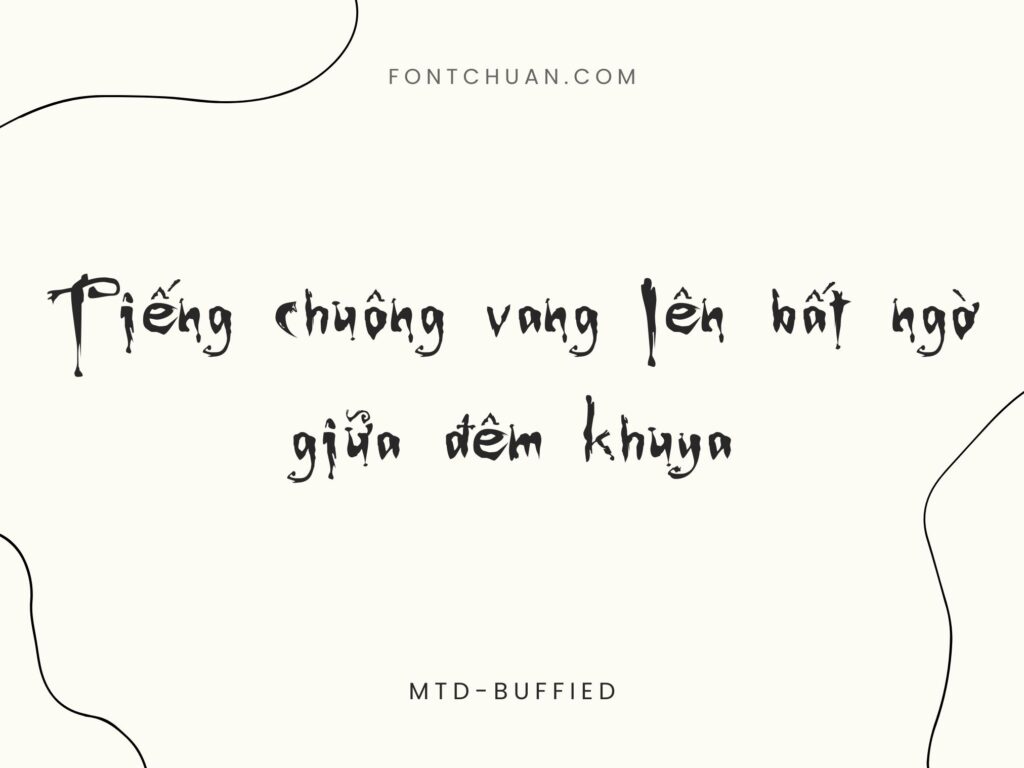
Font MTD Buffied Việt Hóa
Font MTD Buffied là một kiểu chữ trang trí mang phong cách Font Gothic, được thiết kế bởi GemFonts và đã được Việt hóa bởi Mộc Hạ. Font này hỗ trợ đầy đủ tiếng Việt cùng hơn 90 ngôn ngữ khác, mở rộng khả năng ứng dụng trong các thiết kế đa ngôn ngữ. Đây là một trong những phông chữ được cộng đồng thiết kế đánh giá cao và sử dụng trong nhiều dự án sáng tạo, đáp ứng nhu cầu đa dạng của người dùng.
MTD Buffied nổi bật với các đường nét độc đáo và phong cách ma mị, tạo cảm giác huyền bí và ấn tượng. Font rất phù hợp cho các thiết kế liên quan đến chủ đề kinh dị, Halloween, tiêu đề phim, bìa sách, poster và các ấn phẩm đòi hỏi sự khác biệt. Các ngành nghề phù hợp bao gồm quảng cáo, giáo dục, công nghệ và thiệp cưới. Font này cũng lý tưởng cho các sự kiện như Halloween, lễ hội, Tết và Valentine.